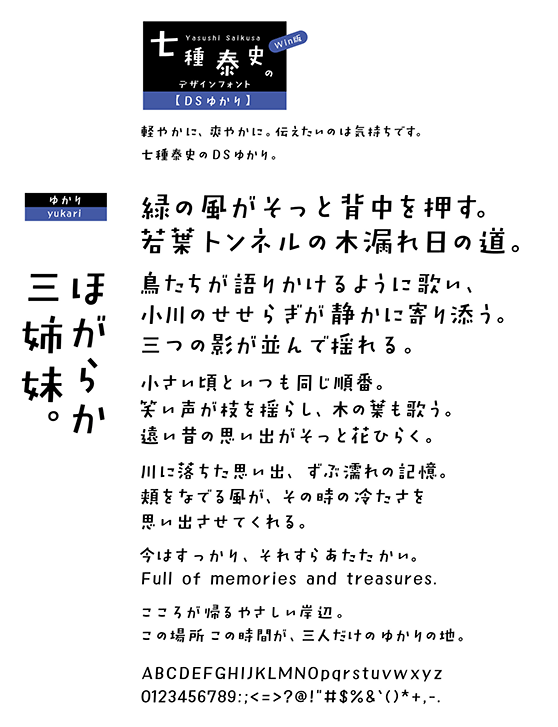
DSゆかり (DS-yukari)
DS-yukari
やさしさ、笑顔、軽快なリズム。DSあかりに次ぐ細いタイプ、ほがらか三姉妹の三女です。
七種泰史/デザインシグナルの紹介
こころのこもった文字創りを目指す七種泰史氏のオリジナルブランド「デザインシグナル」。2008年夏からスタートし、年に2~3書体のペースで開発を進行中。多くのファンが新作を心待ちにする人気のブランド。